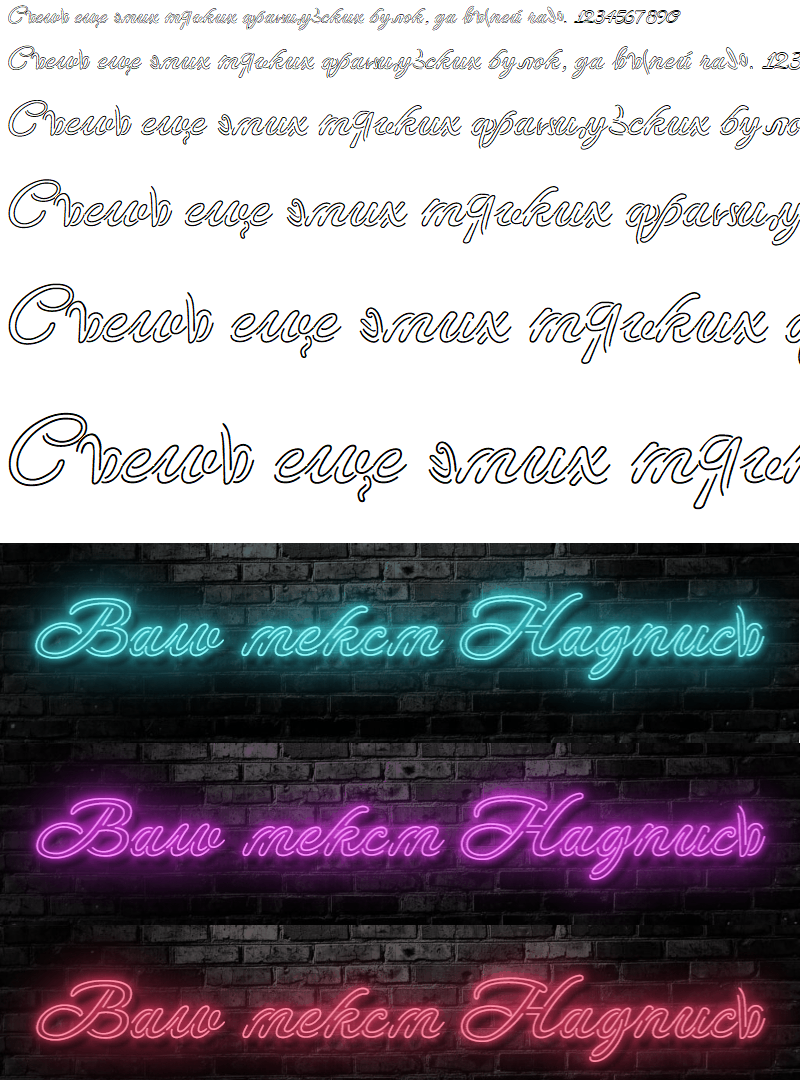
Неоновый кириллический шрифт neon cyrillic font
Крутой красивый неоновый кириллический шрифт тонкие линии. От gfto.ru
Cool beautiful neon Cyrillic font fine lines.